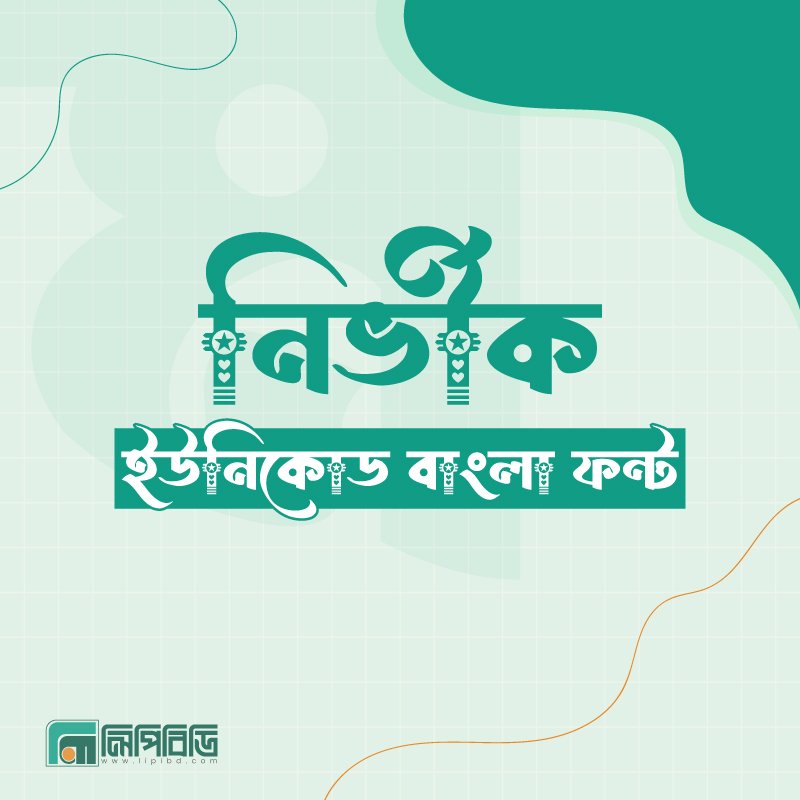
নির্ভীক ইউনিকোড
নির্ভীক ইউনিকোড একটি প্রিমিয়াম মানের বাংলা ইউনিকোড ফন্ট, যা তৈরি করা হয়েছে শক্তিশালী টাইপোগ্রাফি এবং দৃষ্টিনন্দন ডিজাইনের সমন্বয়ে। এই ফন্টের প্রতিটি অক্ষর এমনভাবে ডিজাইন করা হয়েছে যাতে লেখার মধ্যে স্পষ্টতা, ভারসাম্য এবং একটি সাহসী উপস্থিতি অনুভূত হয়। নামের মতোই, নির্ভীক ইউনিকোডের অক্ষরগুলো দৃঢ় এবং আত্মবিশ্বাসী, যা যেকোনো লেখাকে করে তোলে আরও শক্তিশালী ও নজরকাড়া।
নির্ভীক ইউনিকোড (Premium Bengali Font)
এই ফন্টটি বিশেষভাবে উপযোগী হেডলাইন, পোস্টার, ব্যানার, লোগো ডিজাইন, ইউটিউব থাম্বনেইল, সোশ্যাল মিডিয়া ক্রিয়েটিভ, বইয়ের কভার, এবং বিভিন্ন ব্র্যান্ডিং প্রজেক্টে। যেখানে সাধারণ ফন্টগুলো কখনও কখনও শক্ত উপস্থিতি তৈরি করতে পারে না, সেখানে নির্ভীক ইউনিকোড লেখাকে দেয় আলাদা ভিজ্যুয়াল শক্তি এবং ব্যক্তিত্ব।
নির্ভীক ইউনিকোড সম্পূর্ণ ইউনিকোড ভিত্তিক হওয়ায় এটি সহজেই কম্পিউটার, মোবাইল, ওয়েবসাইট, এবং বিভিন্ন ডিজাইন সফটওয়্যার যেমন Photoshop, Illustrator, InDesign, এবং Microsoft Office-এ ব্যবহার করা যায়। বাংলা লেখার সব সাধারণ যুক্তাক্ষর, কারচিহ্ন এবং প্রয়োজনীয় গ্লিফ সুন্দরভাবে সমর্থন করে, তাই দীর্ঘ লেখা টাইপ করলেও এটি স্বাভাবিক ও পরিষ্কার দেখায়।
এই প্রিমিয়াম ফন্টটি তৈরি করার সময় বিশেষ গুরুত্ব দেওয়া হয়েছে অক্ষরের ভারসাম্য, পাঠযোগ্যতা এবং নান্দনিকতার উপর। ফলে এটি শুধুমাত্র একটি ফন্ট নয়, বরং বাংলা ডিজাইন ও টাইপোগ্রাফিকে আরও সমৃদ্ধ করার একটি শক্তিশালী মাধ্যম।
যারা তাদের ডিজাইন বা কনটেন্টে আলাদা পরিচয় তৈরি করতে চান, তাদের জন্য নির্ভীক ইউনিকোড হতে পারে একটি অনন্য পছন্দ। এটি লেখাকে শুধু দৃশ্যমানই করে না, বরং শব্দের ভেতরে সাহস, শক্তি এবং ব্যক্তিত্বের ছাপ রেখে যায়।